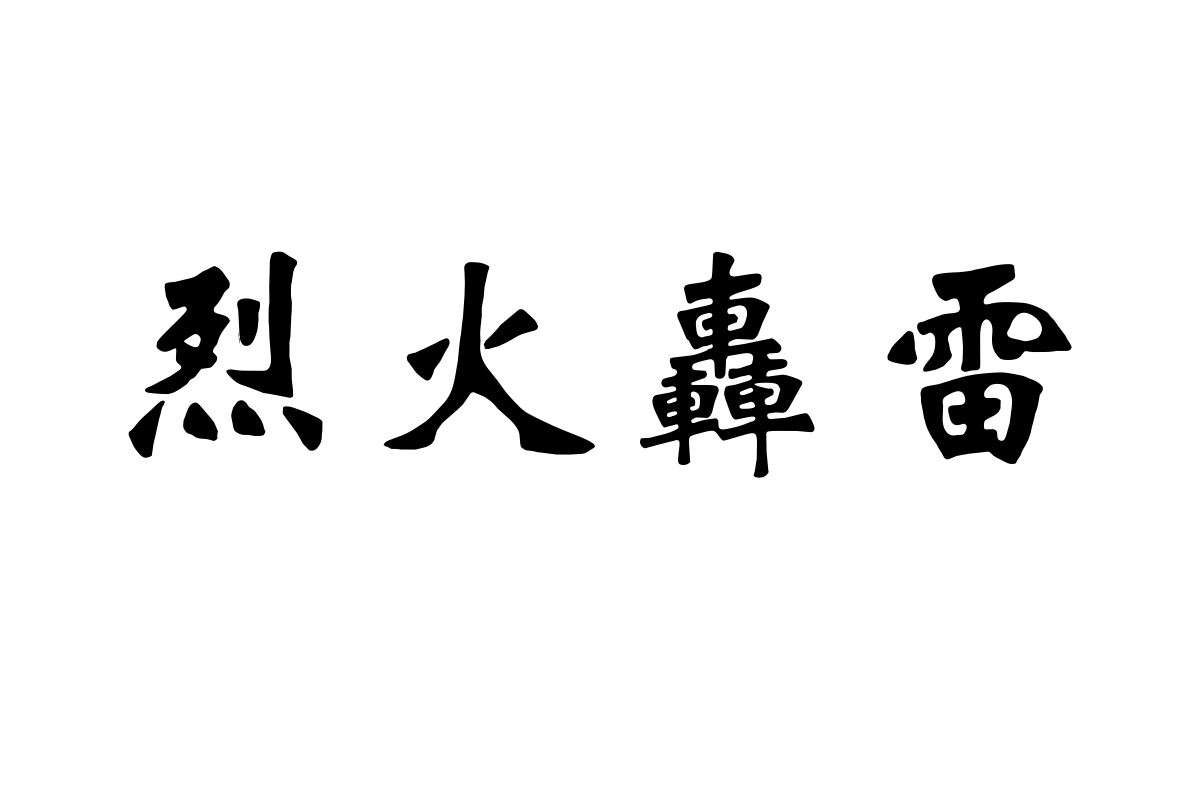
汉仪魏碑繁字体是汉仪公司推出的一款具有浓郁古代书法风格的字体。它源自于魏碑,这是一种起源于东汉的楷书风格,以其刚健有力、笔势雄浑著称。汉仪魏碑繁字体在保留原有风格的基础上,进行了一定程度的优化和创新,使其更适合现代的印刷和设计需求。
这种字体的特点是线条流畅,结构严谨,笔画粗细适中,既有古典的韵味,又不失现代感。它适合用于标题、正文、广告、海报等需要展现庄重、大气氛围的设计场景。同时,由于其笔画的粗细变化较大,也使得它在视觉上具有一定的冲击力,能够吸引观众的注意力。
总的来说,汉仪魏碑繁字体是一款非常适合用于传统文化主题的设计作品的字体,无论是在书籍、杂志、报纸还是网络媒体中,都能够展现出其独特的魅力。